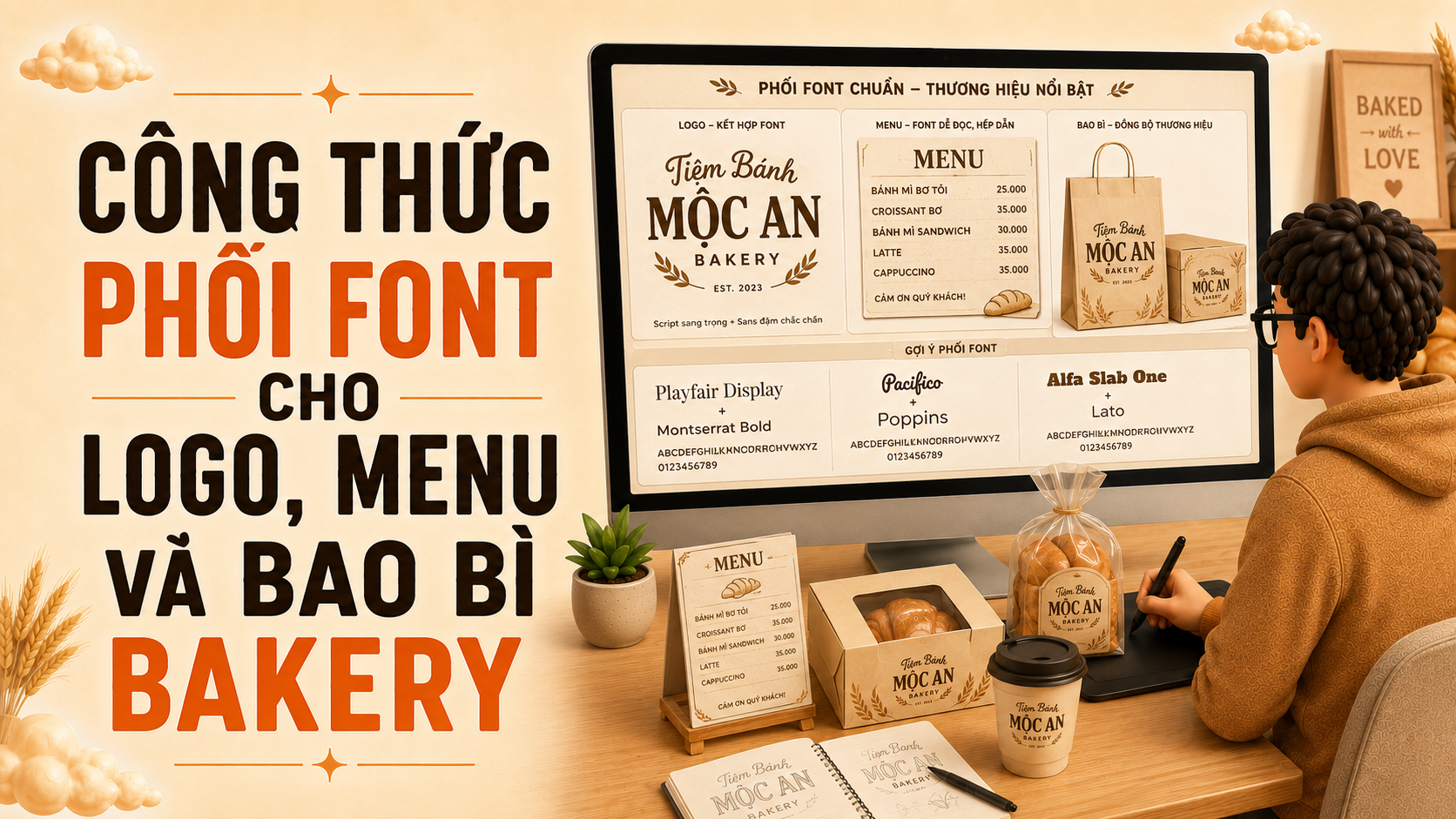
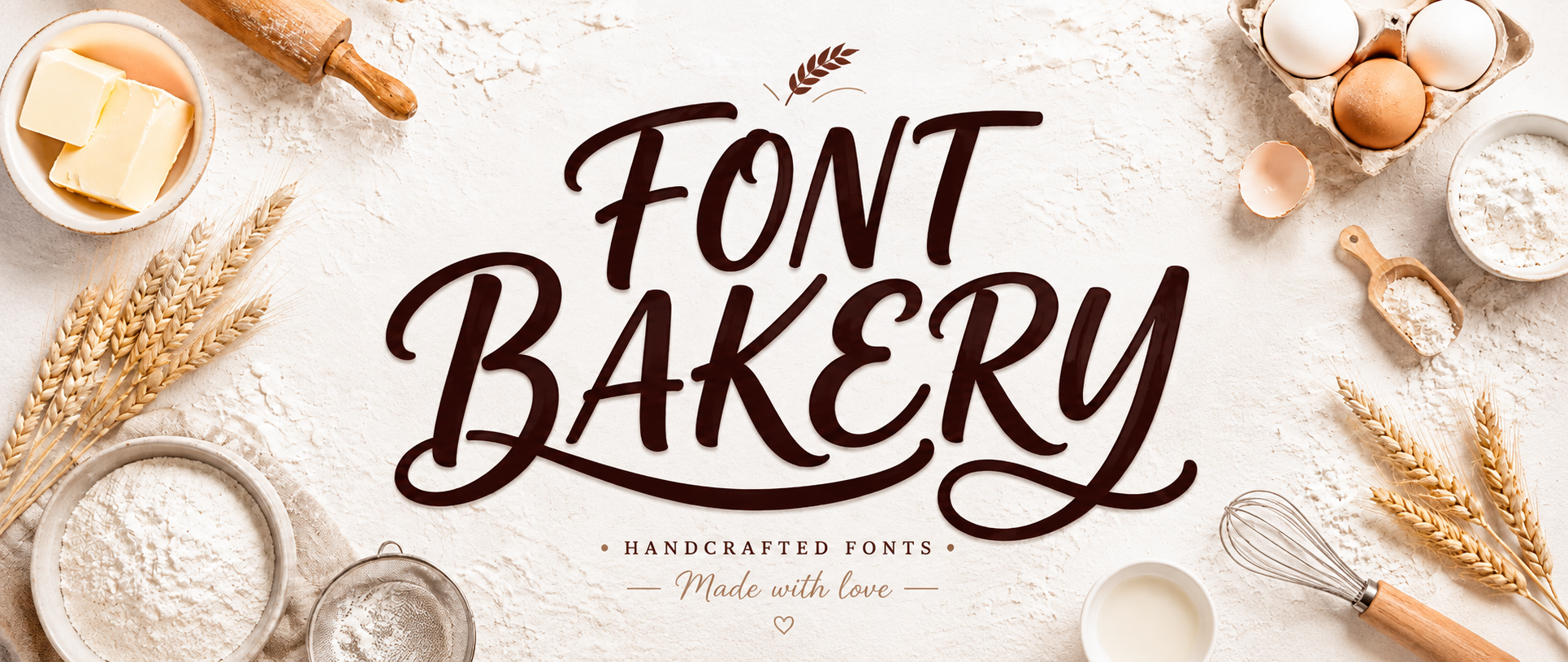
Một tiệm bánh có thể bán bằng mùi thơm, hình ảnh chiếc bánh và cả cách chữ xuất hiện trên logo, hộp bánh, menu, nhãn túi, sticker, poster khai trương. Vì vậy, font chữ bakery, tiệm bánh không chỉ cần đẹp mắt mà còn phải gợi được cảm giác ngon, ấm, thủ công hoặc cao cấp đúng với định vị thương hiệu.
Bài viết này gợi ý các font Việt hóa trên Font S99 phù hợp cho bakery, cake shop, tiệm bánh handmade, bánh sinh nhật, bánh mì, bánh ngọt, dessert box, quán cafe bánh và thương hiệu bánh online. Mỗi font được trình bày thành một dòng riêng với anchor Tải về để bạn dễ tải xuống, thử trên thiết kế thật và chọn nhanh font hợp phong cách.
Khách nhìn một chiếc hộp bánh thường nhận ra rất nhanh thương hiệu đó đang đi theo hướng nào. Font tròn, mềm, mũm mĩm tạo cảm giác ngọt và dễ thương. Font viết tay tạo cảm giác handmade, gần gũi. Font serif thanh lịch giúp tiệm bánh nhìn cao cấp hơn. Font sans-serif sạch lại giúp menu, bảng giá và mô tả sản phẩm dễ đọc.
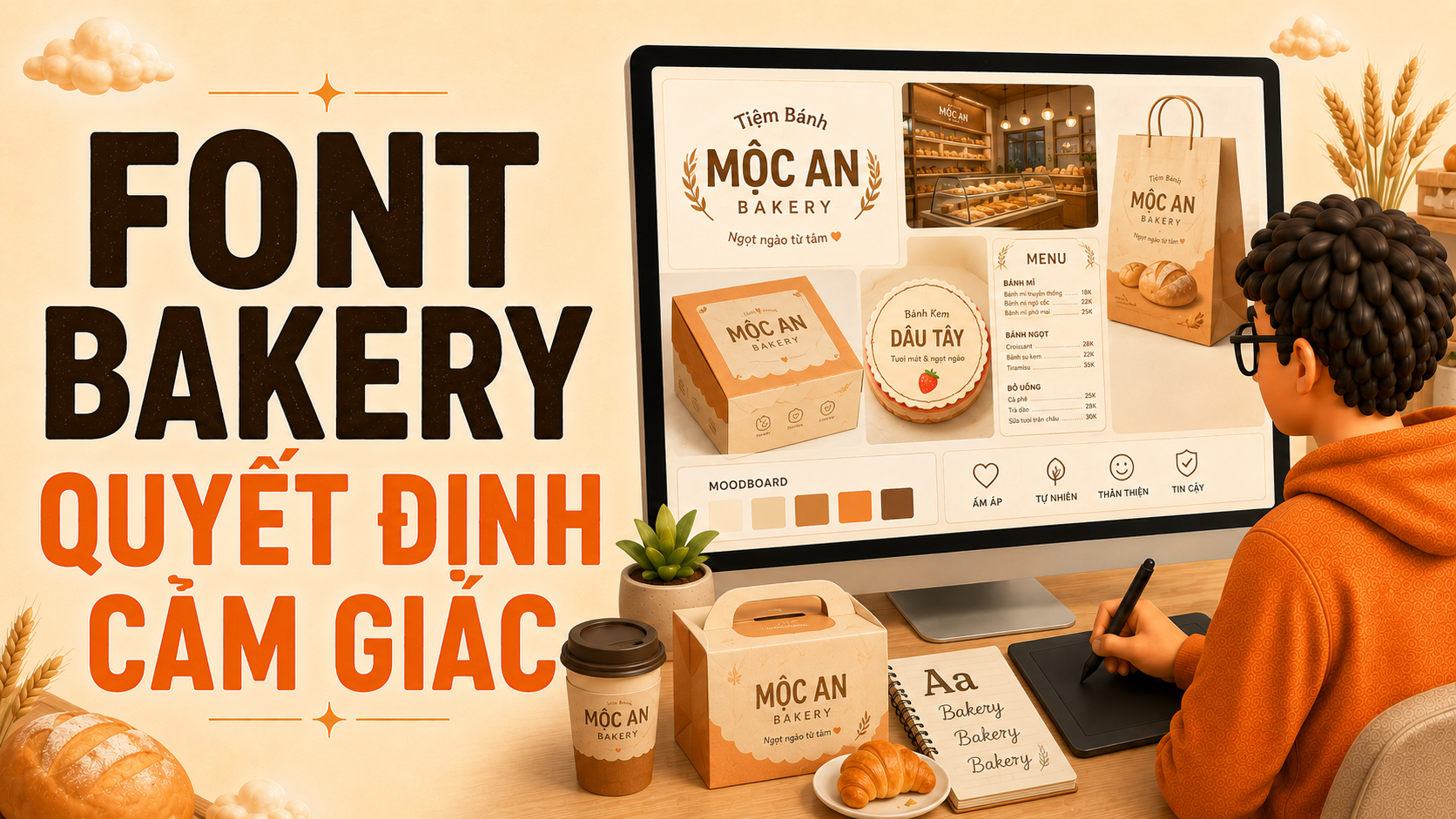
Sai font có thể làm bánh ngon nhưng thương hiệu thiếu gu. Ví dụ, một tiệm bánh mousse cao cấp sẽ không hợp font hoạt hình quá trẻ con. Ngược lại, một tiệm bánh sinh nhật cho trẻ em nếu dùng serif quá nghiêm sẽ mất cảm giác vui. Vì vậy, nên chọn font theo nhóm sản phẩm, khách hàng và kênh bán hàng.
Với tiếng Việt, yếu tố Việt hóa rất quan trọng. Những cụm như bánh kem, bánh bông lan trứng muối, bánh mì bơ tỏi, bánh sinh nhật, trà chiều, hộp quà, ngọt vừa đủ, đặt bánh hôm nay có nhiều dấu. Font lỗi dấu sẽ khiến logo, menu hoặc bao bì kém chuyên nghiệp ngay lập tức.
Bakery handmade cần font mềm và có cảm giác người làm. Tiệm bánh sinh nhật cần font vui, dễ thương, nổi bật. Tiệm bánh Âu, patisserie hoặc dessert cao cấp cần font thanh lịch hơn. Tiệm bánh mì, bánh ngọt take away cần font rõ, nhanh và dễ đọc trên bảng giá.
Menu bánh thường có nhiều tên món, size, topping, nhân bánh, khối lượng và giá. Nhãn hộp, tem dán, sticker và túi giấy lại có diện tích nhỏ. Vì vậy, font headline có thể cá tính, nhưng font thông tin phụ phải rõ, không quá mảnh và không quá rối.
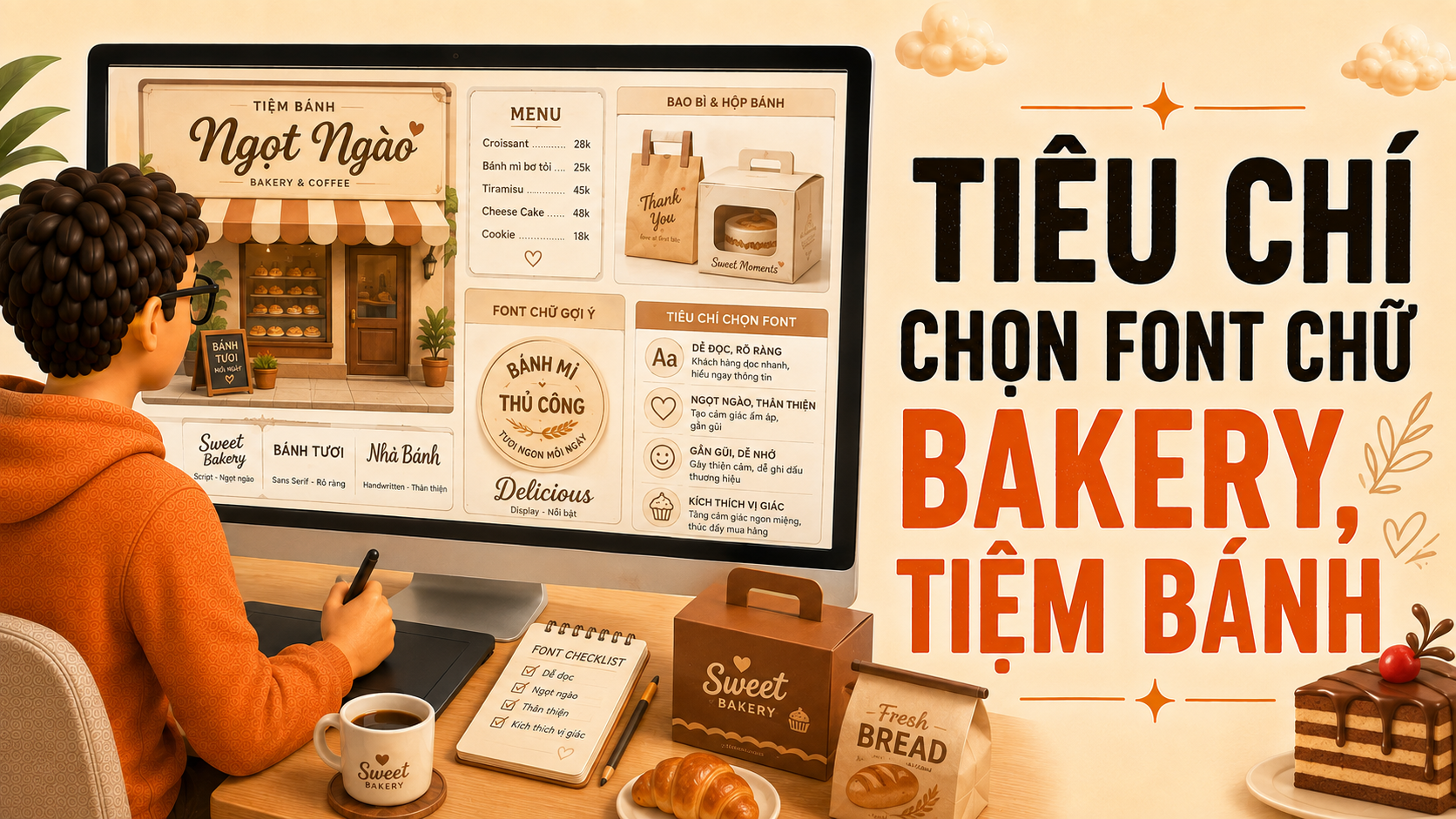
Tên bánh tiếng Việt thường có nhiều dấu. Nếu font không Việt hóa tốt, dấu có thể bị lệch, đè hoặc quá cao. Khi thử font, hãy nhập các cụm như bánh su kem, bánh quy bơ, bánh trung thu, bánh mì hoa cúc, bánh kem dâu để kiểm tra trước.
Một bộ font bakery nên triển khai được trên logo, menu, poster, hộp bánh, nhãn túi, voucher, bảng hiệu, social post, ảnh story và landing page đặt bánh. Nếu font chỉ đẹp ở một poster lớn nhưng khó đọc trên nhãn hộp, chỉ nên dùng làm font phụ.
Nhóm font mũm mĩm hợp với tiệm bánh ngọt, bánh sinh nhật, cupcake, donut, bánh quy, bánh trẻ em, bánh mùa lễ hội và các bài social cần cảm giác vui. Nét chữ tròn giúp thiết kế nhìn mềm, ngọt và dễ nhớ hơn.
Nhóm font này nên dùng cho headline, tên món signature, sticker best seller, poster món mới, tem bánh sinh nhật hoặc nhãn quà. Không nên dùng toàn bộ cho menu dài vì chữ dễ bị nặng mắt. Cách an toàn là dùng font cute cho tiêu đề nhóm, còn mô tả và giá dùng sans-serif rõ.
Nếu thương hiệu dùng màu hồng pastel, kem, nâu sữa, vàng bơ, xanh mint hoặc đỏ cherry, nhóm font mũm mĩm sẽ rất hợp. Hãy để nhiều khoảng trắng quanh chữ để cảm giác ngọt nhưng không bí.
Font viết tay hợp với các tiệm bánh handmade, bánh nhà làm, bánh quy bơ, bánh mì thủ công, cookie box, bánh trung thu handmade hoặc thương hiệu muốn tạo cảm giác gần gũi. Khi dùng đúng, font viết tay làm thiết kế có hơi thở cá nhân hơn, giống một lời nhắn nhỏ đi cùng chiếc bánh.
Font Cherry Feeling - Tải về
Font TH Friendly Stranger - Tải về
Font TH Mortan - Tải về
Font TH Wellyon - Tải về
Nhóm này đẹp nhất khi dùng cho slogan, nhãn hộp, thiệp cảm ơn, chữ ký thương hiệu, tên bộ sưu tập mùa lễ hoặc headline nhẹ. Không nên dùng cho bảng giá, mô tả dài, thành phần hoặc thông tin đặt hàng vì khách sẽ đọc chậm hơn.
Một công thức dễ dùng là font viết tay cho câu cảm xúc như ngọt vừa đủ, baked with love, hôm nay có bánh mới; sau đó dùng sans-serif cho số điện thoại, giá, size bánh, thời gian đặt hàng và CTA.
Nếu tiệm bánh đi theo hướng patisserie, bánh Âu, dessert box cao cấp, bánh cưới, bánh quà tặng doanh nghiệp hoặc trà chiều, font serif sẽ giúp thương hiệu nhìn tinh tế hơn. Nhóm này tạo cảm giác có gu, nhẹ, sang và hợp ảnh bánh tối giản.
Font TH Selvia Genatu - Tải về
Font TH Wrigskan - Tải về
Font TH Erva Esra - Tải về
Font TH Moglan - Tải về
Font Playfair Display Việt hóa - Tải về
Serif nên dùng cho logo, tên thương hiệu, headline catalog, hộp bánh cao cấp, menu seasonal hoặc thiệp quà. Khi dùng cho bánh, hãy phối serif với màu kem, nâu chocolate, đen, vàng champagne, xanh olive hoặc đỏ rượu. Tránh dùng quá nhiều hiệu ứng viền nếu muốn giữ cảm giác sang.
Font chữ bakery, tiệm bánh tốt phải làm người xem cảm thấy bánh ngon, thương hiệu có gu và thông tin dễ đọc. Hãy dùng font cute cho tiệm bánh vui, font viết tay cho handmade, font serif cho bakery cao cấp và font sans-serif cho menu, bảng giá, nhãn hộp, thông tin đặt hàng.